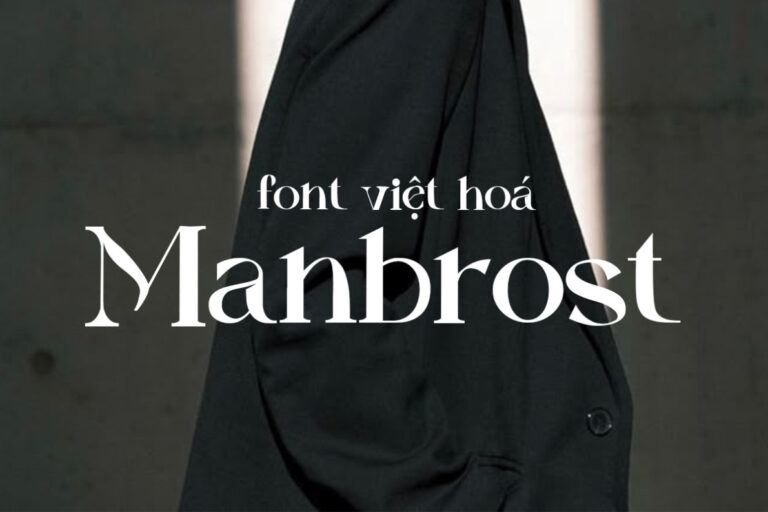
Trong thế giới thiết kế đồ họa hiện đại, việc lựa chọn một bộ Font Chữ phù hợp đóng vai trò quyết định đến sự thành công của tác phẩm. Font việt hoá MJ Manbrost nổi lên như một sự lựa chọn hàng đầu cho những ai đang tìm kiếm sự kết hợp hoàn hảo giữa phong cách cổ điển và hơi thở đương đại. Bộ font này không chỉ mang lại vẻ ngoài chuyên nghiệp mà còn đảm bảo tính thẩm mỹ cao, giúp các nội dung trình bày trở nên ấn tượng và thu hút người xem hơn bao giờ hết.
Đặc điểm nổi bật của Font việt hoá MJ Manbrost
MJ Manbrost là một bộ phông chữ thuộc phong cách Serif với các đường nét tinh tế, mạnh mẽ nhưng không kém phần uyển chuyển. Khi được thực hiện dự án Font việt hoá MJ Manbrost, đội ngũ thiết kế đã tinh chỉnh kỹ lưỡng các dấu tiếng Việt để đảm bảo sự cân đối, không làm mất đi linh hồn vốn có của bảng chữ cái gốc.
Ứng dụng đa dạng trong giáo dục và thiết kế
Nhờ cấu trúc rõ ràng và dễ đọc, bộ font này cực kỳ phù hợp cho các bạn học sinh, sinh viên khi làm bài thuyết trình hoặc thiết kế báo tường. Ngoài ra, các thầy cô giáo cũng có thể sử dụng MJ Manbrost để soạn thảo tài liệu giảng dạy, giúp bài học trở nên sinh động và chuyên nghiệp hơn. Sự linh hoạt của nó cho phép ứng dụng từ thiết kế logo, bìa sách cho đến các ấn phẩm truyền thông học đường.